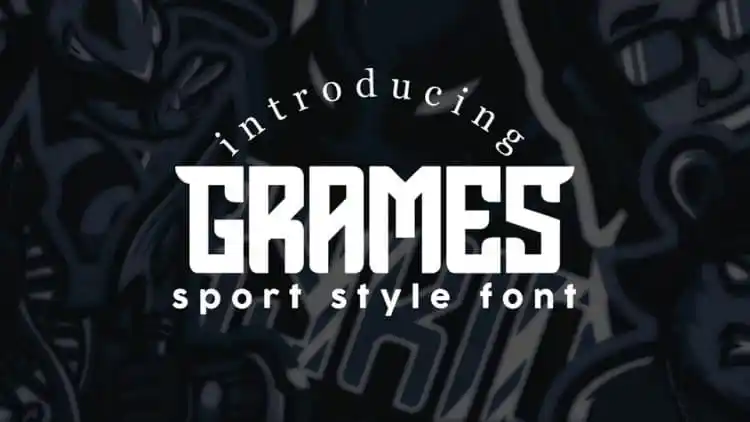
Aqui está uma descrição em português do Brasil para a página de download da fonte ‘Grames Sport Style Font’, seguindo as instruções: Descobrimos uma nova fonte chamada Grames Sport Style, criada pelo designer Hamilton. Esta é uma fonte serif que traz um toque moderno e elegante aos estilos urbanos mais agitados. Ideal para criar posters de esportes vibrantes ou capas de revistas com um visual dinâmico e robusto, esta fonte oferece um forte impacto inicial, combinando modernidade com uma estrutura masculina forte. Perfeita para publicidade ambulante, cabeçalhos de notícias e headlines em jornais, Grames Sport Style também é uma excelente escolha para elementos gráficos que precisam de um design atraente para posters urbanos. A fonte traz estilo à sua marca ou projeto personalizado, transmitindo um olhar atrevido e moderno que se destaca em qualquer formato. Se você está procurando por uma opção visual moderna e robusta para seus projetos em esportes ou design gráfico urbano, a Grames Sport Style pode ser o elemento perfeito. Seu design elegante e sua simplicidade funcional garantem um resultado impecável, tornando-a uma escolha confiável para qualquer projeto que você está criando.